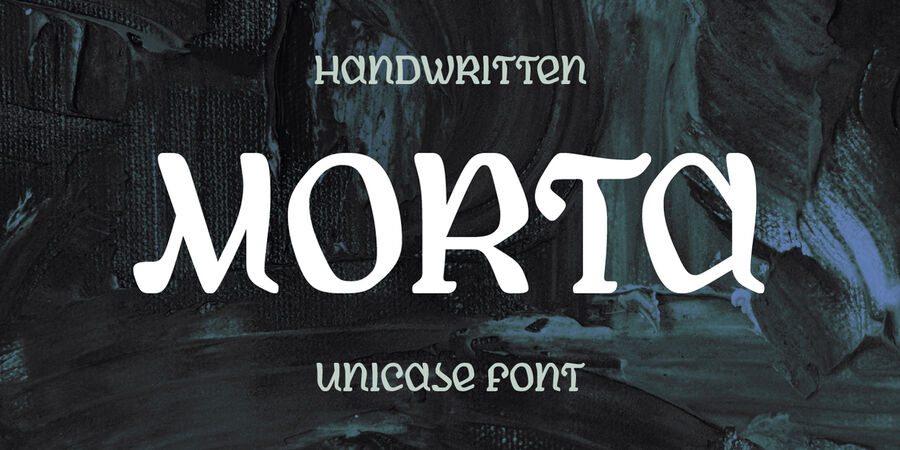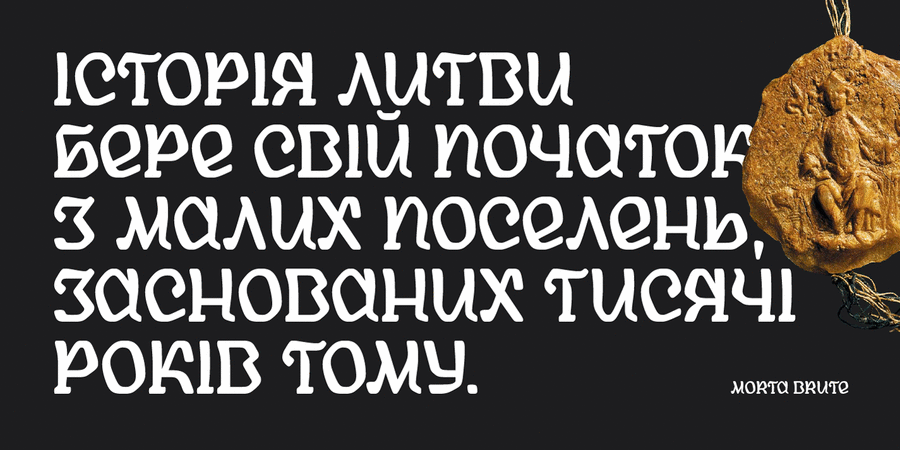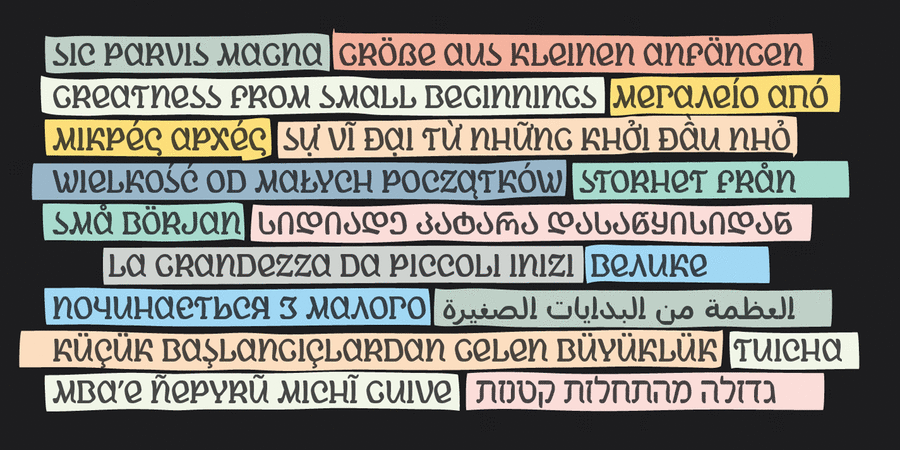
Morta – це рукописний юнікейс шрифт із незначним каліграфічним впливом. Його дизайн, як багатовікове холодне темне каміння, має різьблені грані та стерті кути, та представлений двома стилями: більш розбірливим «Brute» для загального використання та більш контрастним «Grace» для великого розміру тексту.
Накреслення: Brute, Grace. Промо зображення використовують живопис “The Dedication” Едмунда Лейтона, живопис “Ідилія” Миколи Пимоненка, фото Steve Johnson із Pexels та Mett Brett із Unsplash, поезію “Що в нас було?” Ліни Костенко, “The Dedication” Вільяма Шекспіра, та ілюстрації Михайла Рафайлика. Шрифт розробив Михайло Рафайлик у 2023 році та значно розширив мовну підтримку у 2024. Світ ловив мене, та не спіймав!